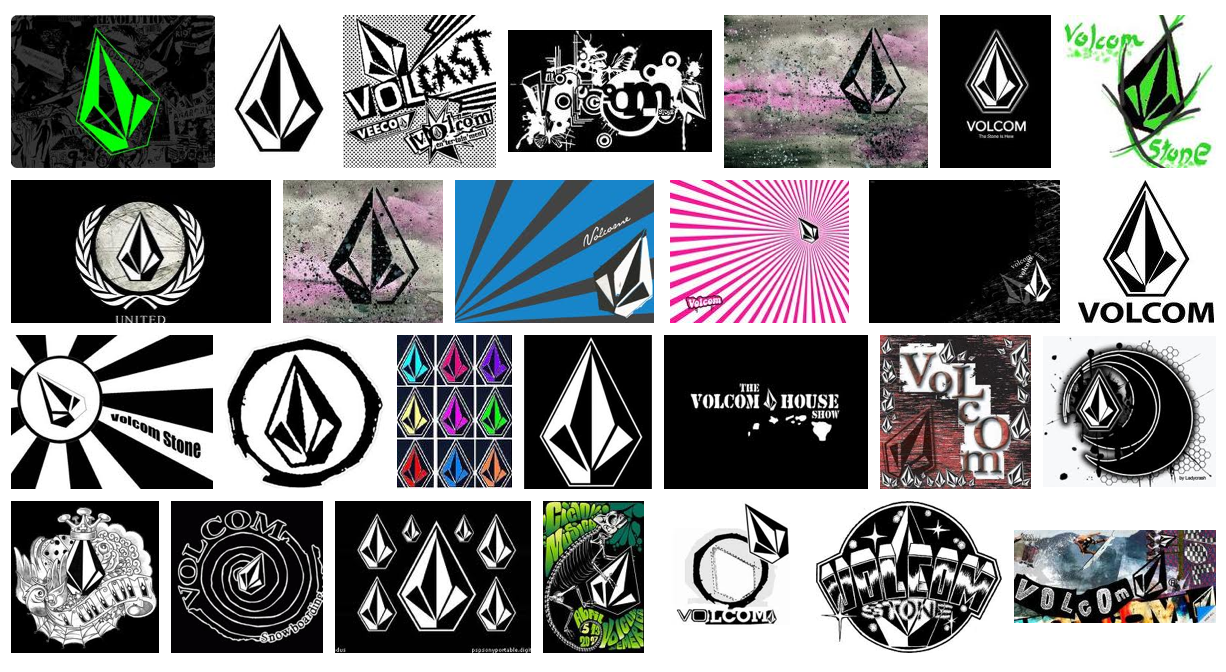
Beispiele gesucht für illustrativ/spielerisch eingesetzte Logoelemente
wir sind grade auf der Suche nach Argumentation und Praxis-Beispielen dafür, dass ein Logo-Element innerhalb eines definierten Corporate Designs auf definierte weise auch als "illustratives Element" eingesetzt werden kann / "darf".
Heißt z.B.:
- Es gibt auf einer Titelseite das ganze, unversehrte Logo des Unternehmens, zusätzlich wird ein Teil des Logos (die Bildmarke) in deutlich größerer Größe als grafisches Element über den Formatrand hinaus angeschnitten.
- das Logo dient als Element für eine Textur.
- ...
Wir haben grade einen solchen Fall (wie in Beispiel 1), jetzt schießt jemand von außen mit dem Killer-Argument quer, dass ein Logo "niemals angeschnitten werden darf".
Es geht uns einfach darum, zu zeigen, dass das "niemals" relativ ist, und es dafür gute Beispiele gibt (dass das Logo nicht willkürlich missbraucht werden darf, ist natürlich klar). Nur: die haben wir nicht grade in der Hosentasche parat ... Vielleicht lassen sich ja hier ein paar zusammentragen.
«Ein Logo darf niemals angeschnitten werden!» ist kein Killerargument, sondern allerhöchstens eine Behauptung. Meines Erachtens bestimmt der Inhaber einer Marke zusammen mit dem Urheber, was mit dem Logo alles angestellt werden darf und was das Zeichen absolut nicht erträgt. Das hängt natürlich auch vom Wesen einer Marke ab, wofür sie steht, wen sie anspricht und so weiter.
Nicht nur Volcom (siehe Anhang) ist zum Beispiel extrem frei in der Handhabung. (zum brandifesto)
Solche dogmatischen Aussagen werden sehr gerne von Leuten getroffen, die es lieben, komplexe Regelwerke aufzustellen und dann deren ausnahmslose Einhaltung einzufordern (die schön bequem ist, weil man nicht denken muss). Gute Gestaltung resultiert für mich aber nicht aus der widerspruchslosen Anwendung einmal getroffener Vorgaben, sondern aus der immer wieder aufs Neue offenen und sensiblen Reaktion auf visuelle Gegebenheiten. Wichtig ist dabei das gewissenhafte Hinterfragen von Regeln und deren Gültigkeit im jeweiligen Kontext. :-)
Ein Beispiel wär die Telekom, die ja auch mit Ihren Pink-Kästchen dekorativ spielt und nicht nur die Logoversion mit den 4 Kästchen zuläßt.
Das ist genau das Problem: Eine Art "Regelritter" kommt und sagt "das darf man nicht". Das lässt sich am besten entkräften mit "Aber die erfolgreichen Marken A, B und C machen genau das, und ja, sie leben noch."
Ich suche Beispiele von mittleren und größeren "seriösen" Unternehmen.
Telekom passt (wenn ich denn ein entsprechendes Beispiel finde).
Volcom ist zwar das perfekte Anwendungsbeispiel, wird aber den Kunden nicht überzeugen, denn sein CI-Handbuch heißt tatsächlich CI-Handbuch, nicht Brandifesto ... (also er betreibt keine Lifestyle-Marke).
H & M macht das doch auch auf den Versandtaschen und Tüten ...
... oder sind die beiden auch zu sehr Lifestyle :-?
Nicht richtig angeschnitten, aber:
JOOP! verwendet seine Bildmarke (stilisierte Kornblume) als ornamentales Rapport-Muster auf Stoffen, Einrichtungsgegenständen etc.
Diverse Zeitschriften spielen damit, dass sie Teile des Logoschriftzuges verdecken, beispielsweise, wenn der Kopf eines Models vor den Buchstaben steht.
Marlboro macht das Gleiche, da steht/stand der Cowboy auf Plakaten und Anzeigen auch regelmäßig vor dem Logoschriftzug.
Das ist genau das Problem: Eine Art "Regelritter" kommt und sagt "das darf man nicht". Das lässt sich am besten entkräften mit "Aber die erfolgreichen Marken A, B und C machen genau das, und ja, sie leben noch."
Hmmm, das hängt natürlich vom Kunden ab, aber mir drängt sich sofort die Frage auf warum man das nicht machen darf? Über Argumente kann man diskutieren, bei Aussagen kann man selber eine andere Meinung haben und wenn Aussagen sich nicht mit Argumenten untermauern lassen, dann würde ich als Kunde es mir gut überlegen, wieviel Wert ich einer solchen Aussage beimesse. Der Erfolg anderer Firmen ist dann natürlich ein Gegenargument welches im Zweifelsfall eine wackelige Position zum Einstürzen bringt.
Der Wert dieser Aussage liegt in unserem Fall hauptsächlich darin, dass der, der es gesagt hat ein hochgeschätzter (und auch erfolgreicher) Geschäftspartner ist – dessen Logo *nicht* angeschnitten ist. Derjenige hat halt mal von einem Grafiker die Argumentation gehört, dass das Firmenlogo das erste Erkennungszeichen eines Unternehmens ist, und unbedingt unversehrt bleiben muss (ich kann ja auch diese Position gut begründen, sie hat nur keine Allgemeingültigkeit).
Jetzt ist unser Kunde verunsichert und hat eben nachgefragt.
Aber ein paar zusätzliche Anwendungsbeispiele helfen dabei natürlich ungemein weiter.
Könnte dem Kunden zeigen, dass manchmal gar kein starres Logo von Nöten ist. Variationen tragen durchaus dazu bei, ein prägnantes Gestaltungsmerkmal zu werden.
Ich denke letztlich ausschlaggebend waren Telekom und speziell Hypo Group (ähnlich "sachliche" Gestaltung wie in unserem Fall).